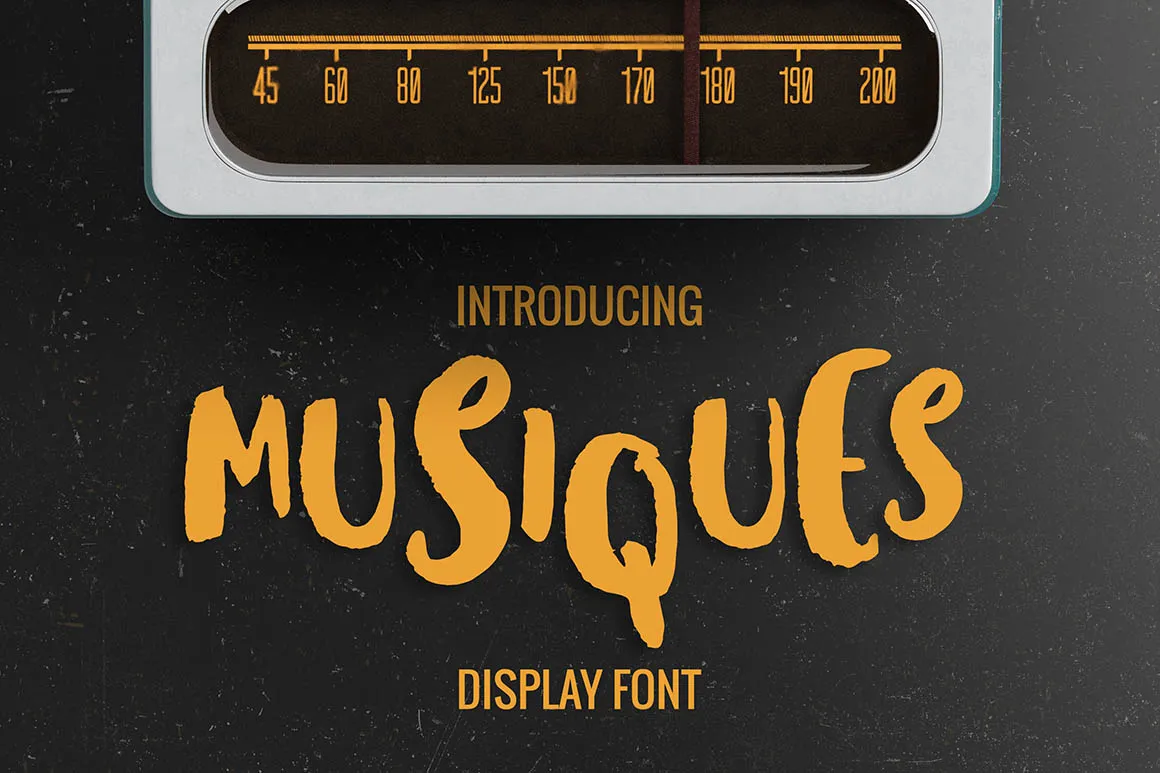
Musiques Brush Font – Download Grátis
A fonte Musiques Brush é uma criação inovadora para designers que valorizam a elegância do estilo manuscrito antigo. Ideal para elementos de marca, citações typográficas sobre fotos e design de capas de livros ou embalagens, ela foi projetada pelo designer Yasir Ekinci com um toque vintage e graciosamente handwritten. A fonte é uma combinação única de caracteres maiúsculos e minúsculos, incluindo gírias de pontuação e números, adaptados para diferentes idiomas do mundo inteiro. O design contempla sets estilísticos para várias letras minúsculas principais, tornando-a perfeita para um vasto leque de projetos gráficos. Se você está em busca de uma fonte que combine elegância com uma pitada nostálgica e autêntica graça manuscrita, Musiques Brush é uma opção incrível a considerar.